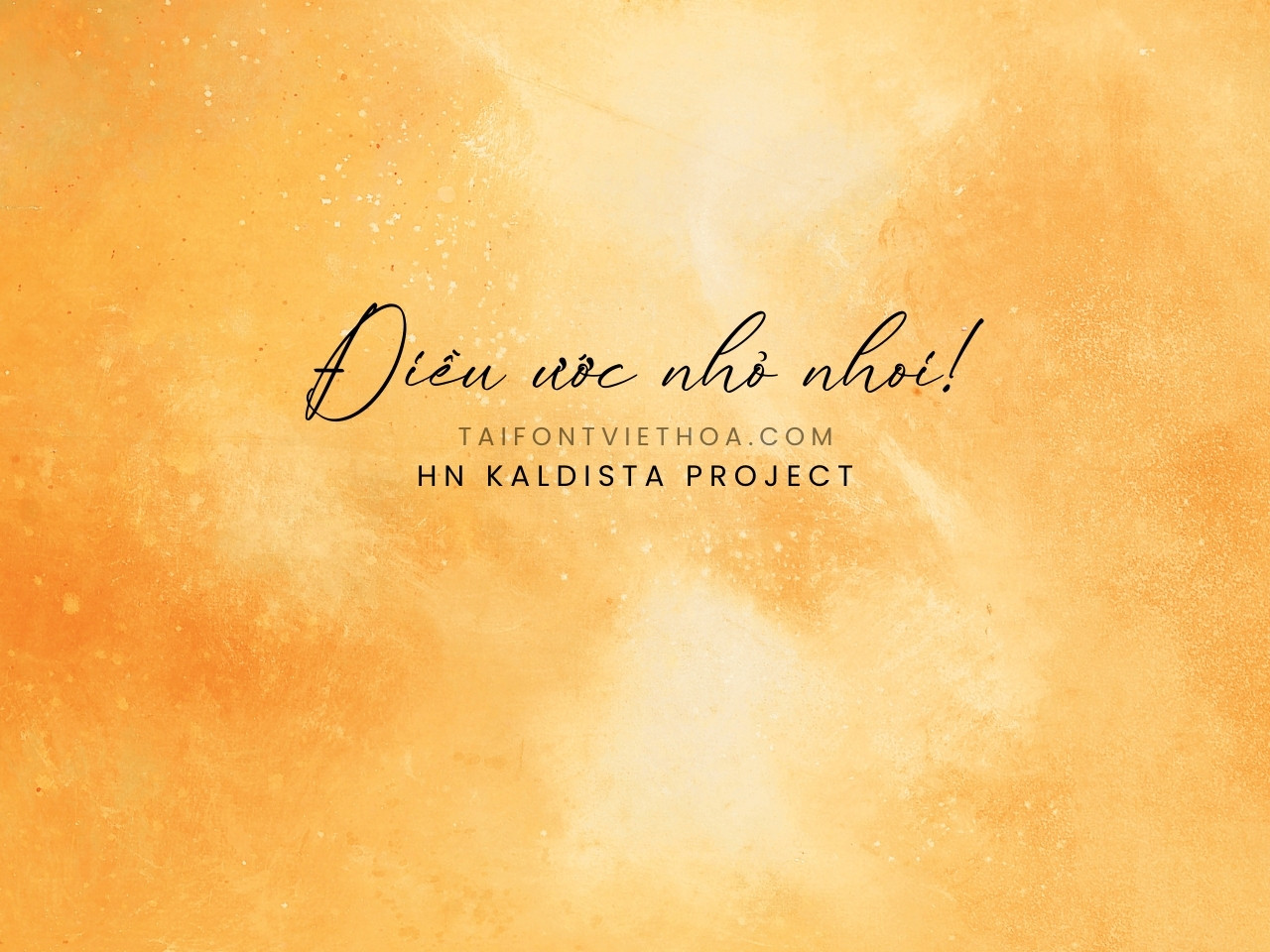
Font việt hóa Kaldista Project
Giới thiệu font Kaldista Project – Phong cách chữ ký viết tay hiện đại
Kaldista Project là một kiểu font chữ ký mang phong cách viết tay đầy ngẫu hứng, được thiết kế bởi Font Fabric – đơn vị nổi tiếng với các font mang tính ứng dụng cao trong thiết kế đồ họa, thương hiệu và sáng tạo nội dung. Với các nét viết tự nhiên, mềm mại và duyên dáng, Kaldista Project truyền tải cảm xúc cá nhân, giúp tăng tính chân thực cho các thiết kế mang yếu tố con người. Phiên bản Việt hóa do Huy Nam thực hiện, hỗ trợ đầy đủ tiếng Việt và hơn 70 ngôn ngữ khác. Font đã được taifontviethoa.com chọn lọc, sưu tầm và chia sẻ đến cộng đồng như một bộ font lý tưởng cho các thiết kế đậm chất nghệ thuật và mang dấu ấn cá nhân sâu sắc.
Đặc điểm cảm xúc và ứng dụng của Kaldista Project
Kaldista Project có đặc điểm nổi bật là nét viết liền mạch, đậm chất chữ ký tay, mang lại cảm giác chân thực và gần gũi. Font phù hợp với các thiết kế như thư mời, thiệp cưới, logo thương hiệu cá nhân, bao bì mỹ phẩm thủ công, tiêu đề trang blog hoặc các sản phẩm nghệ thuật số. Tính cá nhân hóa cao giúp font này đặc biệt phù hợp với các ngành nghề như ảnh cưới, mỹ phẩm, ẩm thực thủ công, giáo dục nghệ thuật và các chiến dịch thương hiệu mang tính tự truyện. Ngoài ra, font cũng rất lý tưởng để sử dụng trong dịp Giáng sinh, Tết, Valentine hay các sự kiện nghệ thuật và lễ hội mang sắc thái riêng biệt.